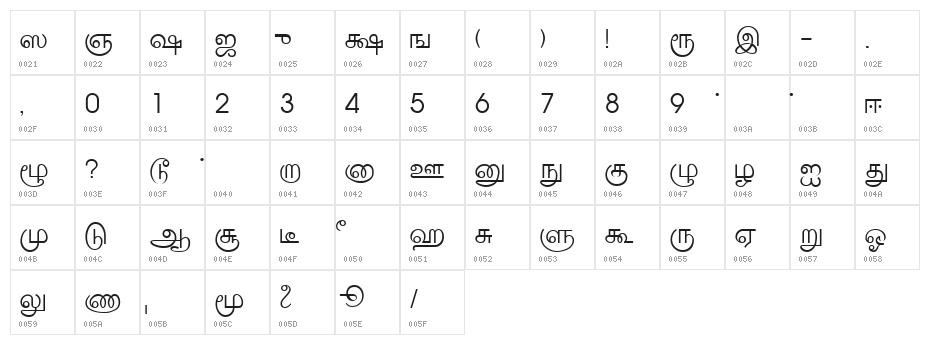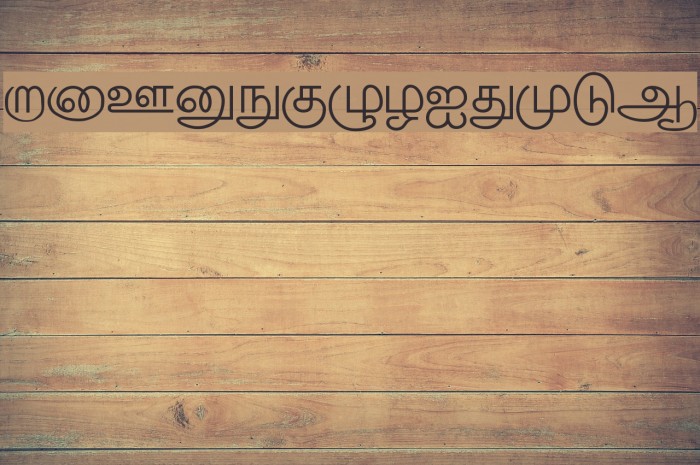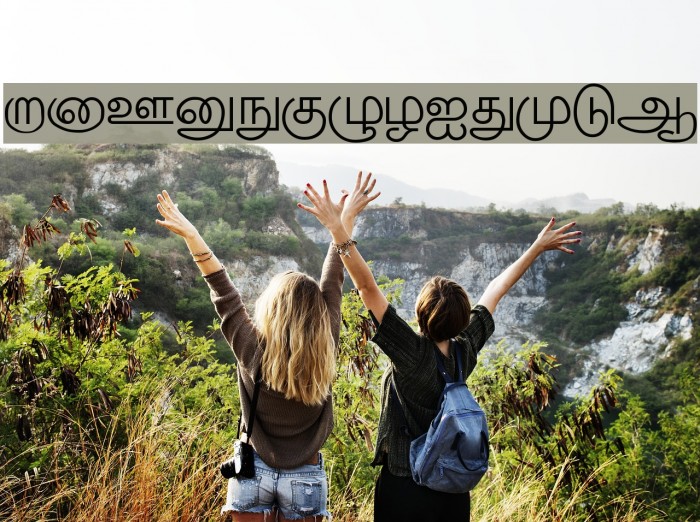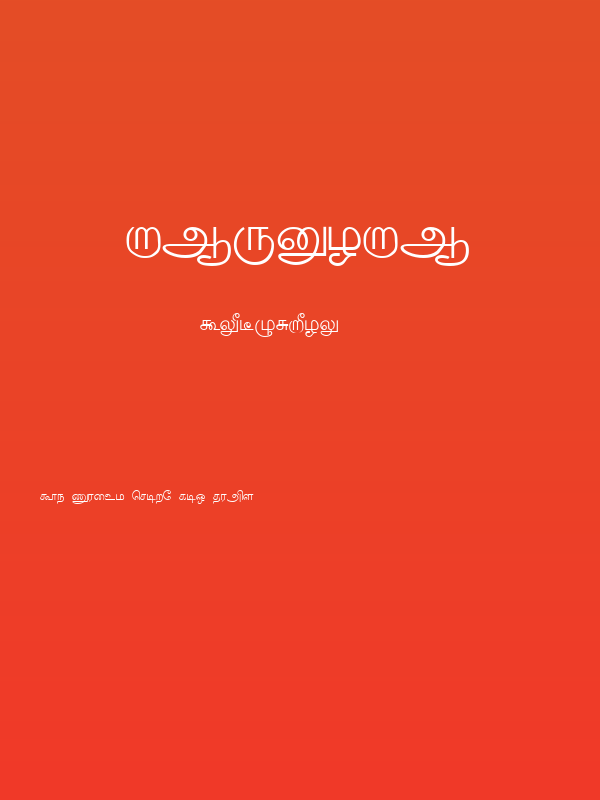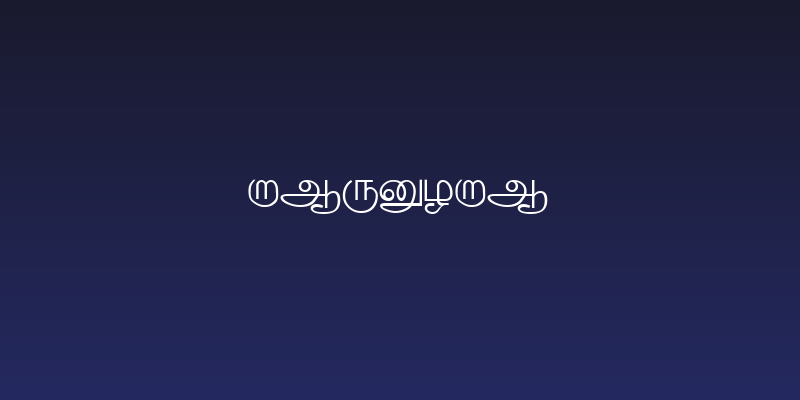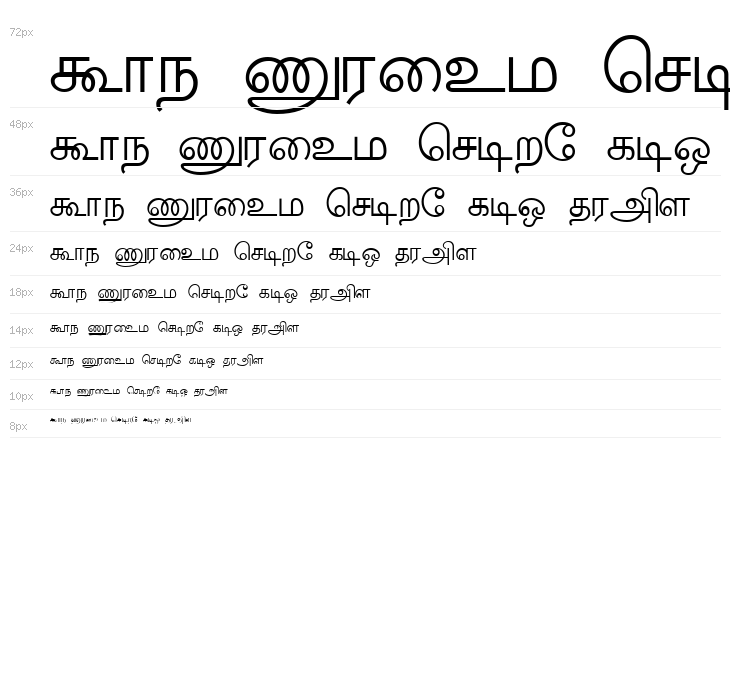
Amudham Font
| Anwendungsfall | Headlines, Body text, Logos |
| Vorgeschlagene Projekte | This font is perfect for branding, signage, digital content, and print media where a modern and clean appearance is desired. |